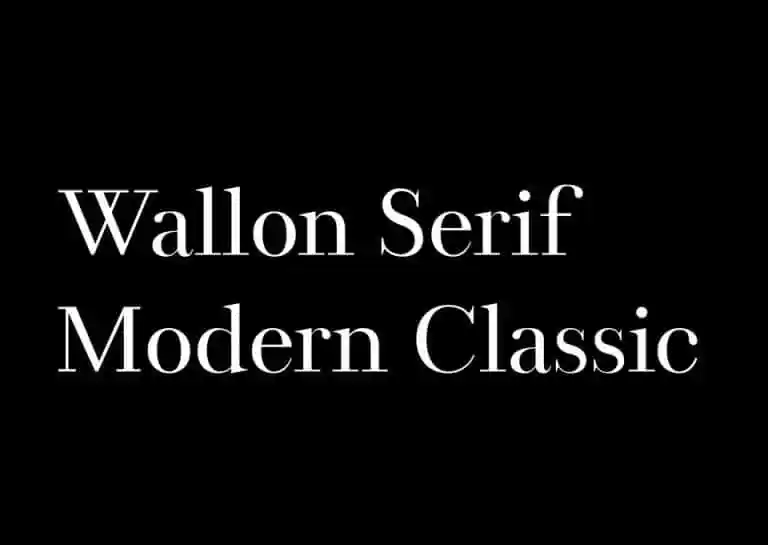
A Wallon Serif é uma fonte serif inspirada nos padrões antigos da serif e no desenho moderno dos caracteres atuais. Foi criada pelo talentoso designer Jeong-il Seok, que incorpora elementos contemporâneos nas linhas detalhadas do design de fontes. Este estilo serif tem contraste alto, se apropriando das características de transição tipográfica e incorporando aspectos contemporâneos em forma e detalhes da linha. É perfeito para tornar suas legendas mais chamativas, ilustrar sua identidade visual de marca, editoriais, anúncios e muito mais. Se você procura uma fonte serif com um toque moderno que ainda mantém a elegância clássica do estilo tradicional, então a Wallon Serif pode ser exatamente o que você precisa.